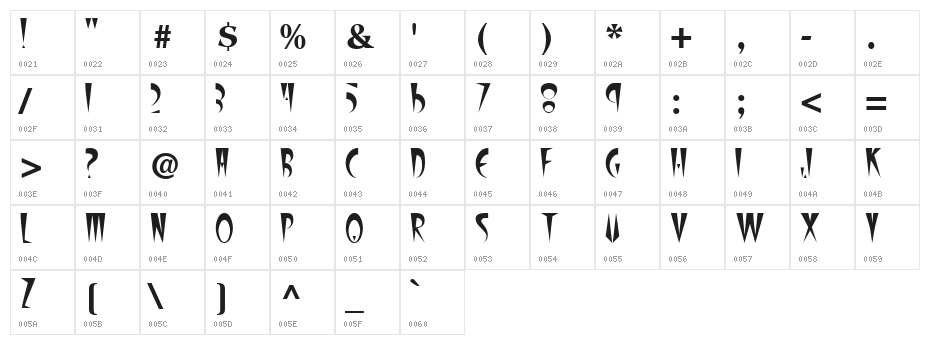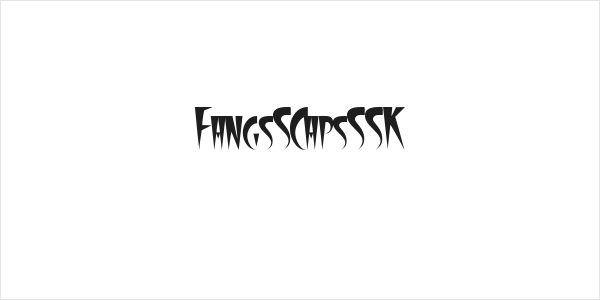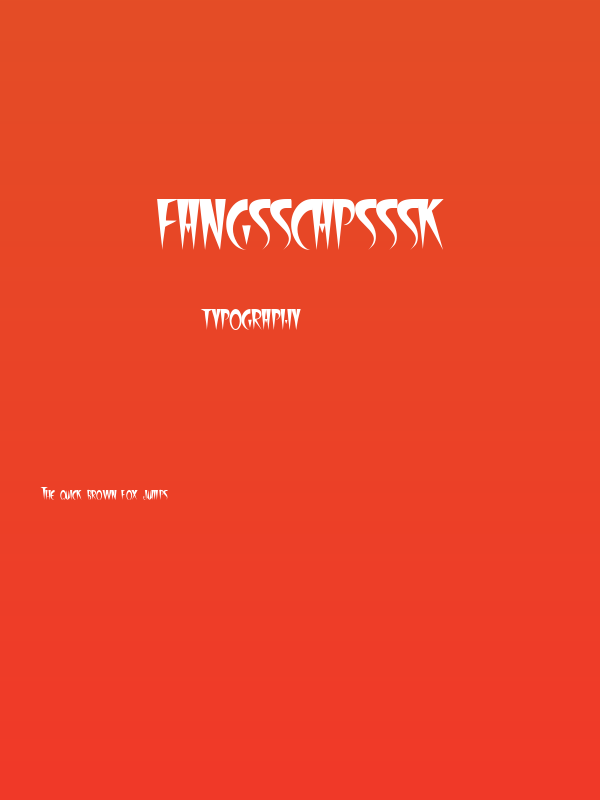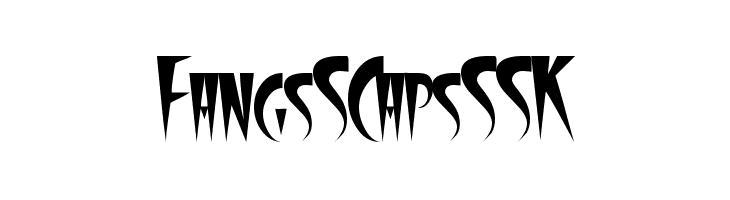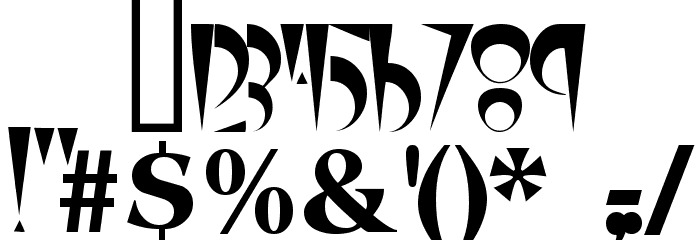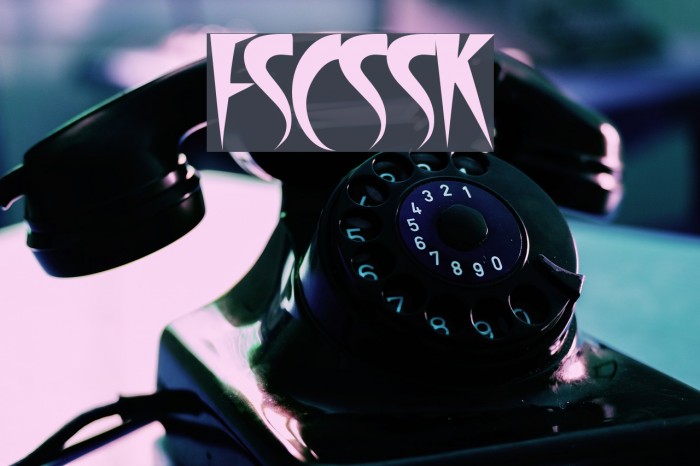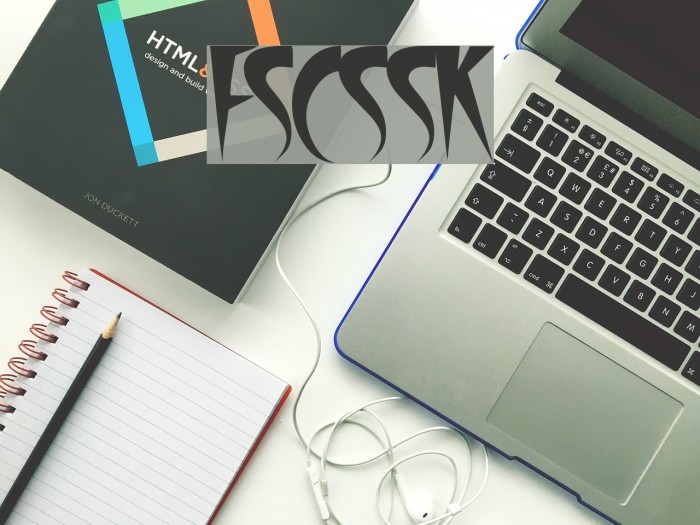
FangsSCapsSSK Font
| Рекомендуемые проекты | Ideal for horror-themed designs, movie posters, video game titles, or any project needing a bold, edgy look. |